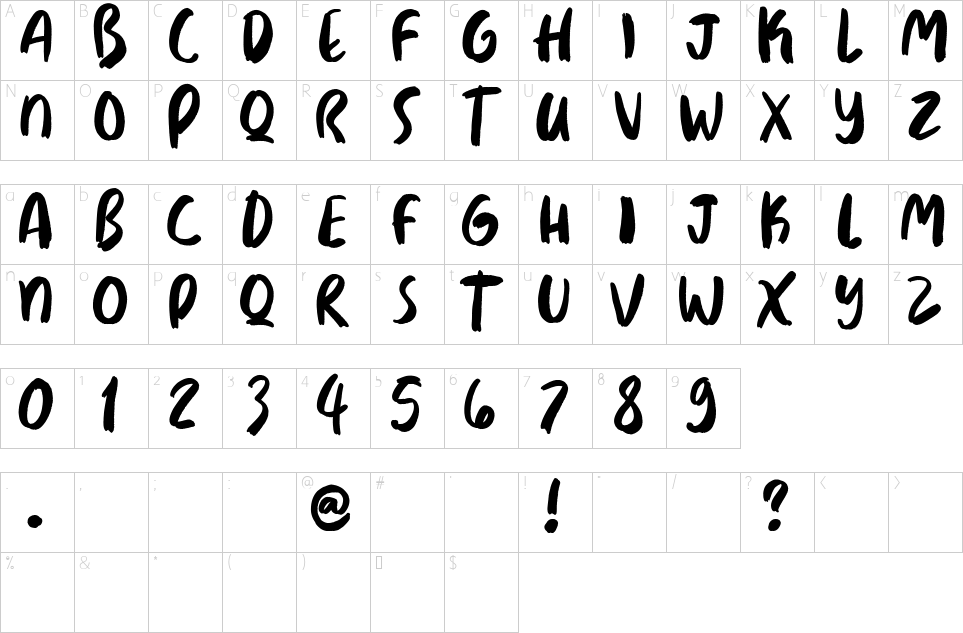
Breakfast Crew Font
Descubra a beleza única e vibrante do Breakfast Crew Font para seu próximo projeto design. Esta elegante fonte foi criada por The Branded Quotes e tem sido baixada pelo número recorde de 228 vezes. Com um design que encanta, essa font é ideal tanto para textos semifonte quanto para headlines, tornando-a uma opção incrível para aqueles buscando uma paleta de cores vibrante e interessantes para seus projetos gratuitos em Windows e Mac. Comece a explorar hoje e transforme seu design digital!